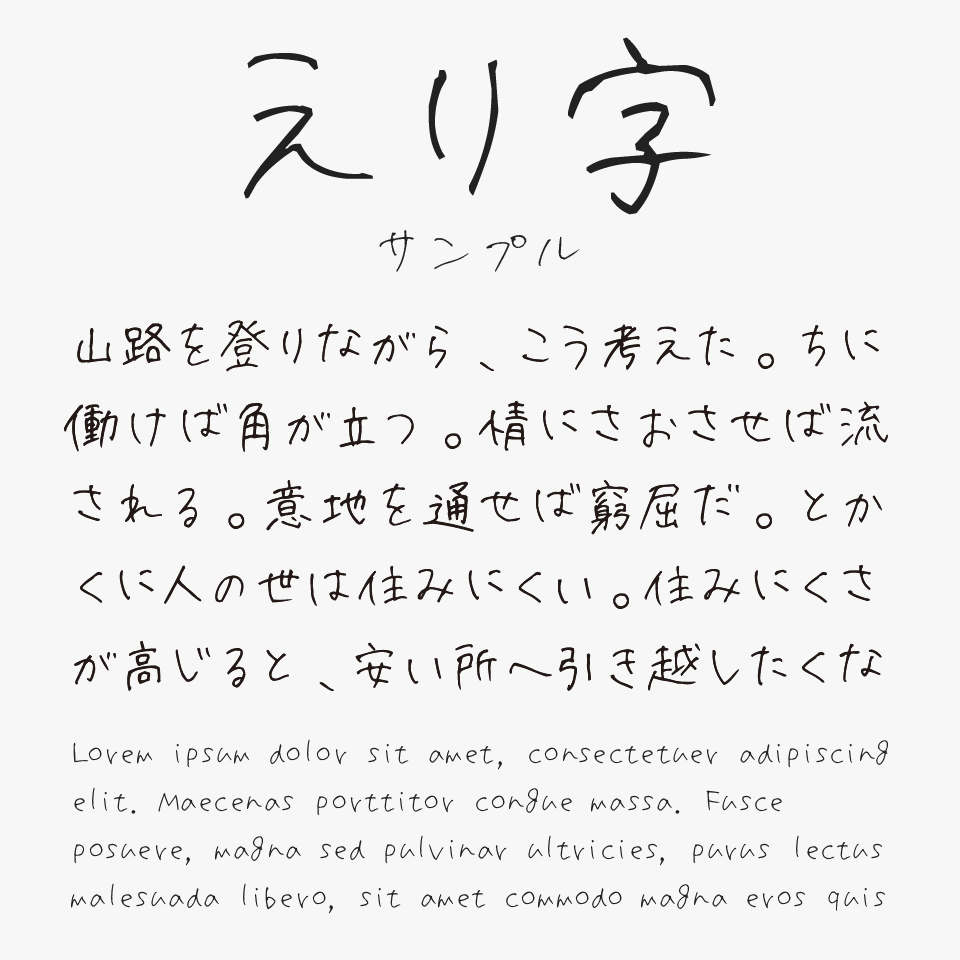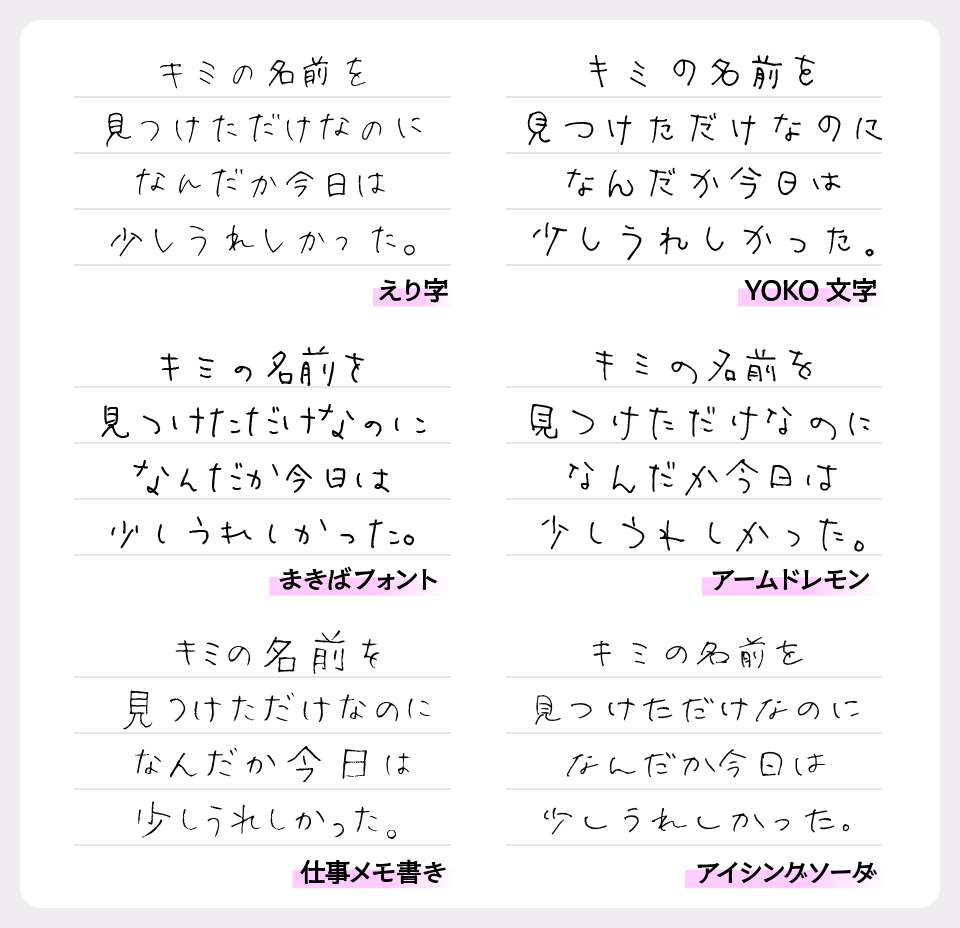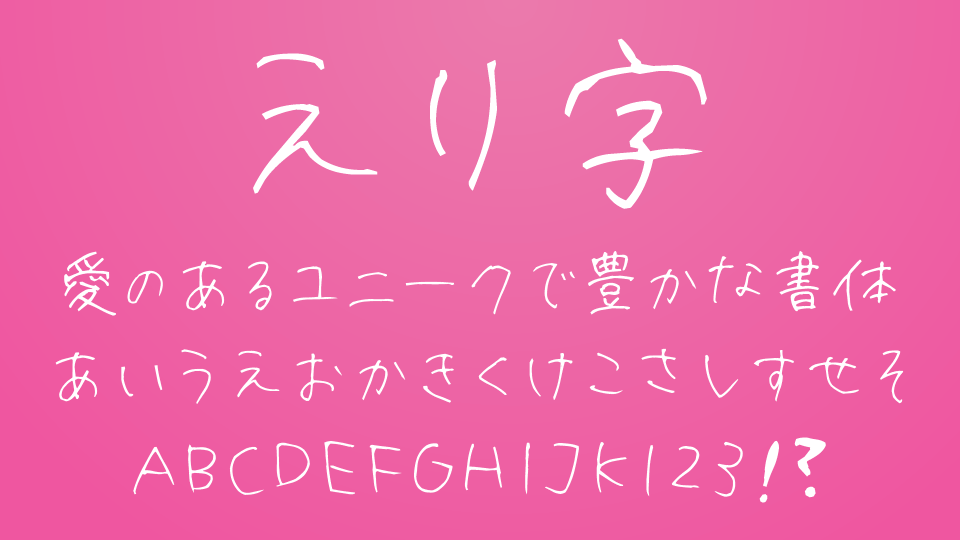
えり字
えり字フォントは、女子高生がボールペンでノートや手紙に書いたような、小ぶりで可愛らしい字が特徴の手書きフォントです。
文字全体に自然な丸みがあり、気取らない親しみやすさを感じられるデザインになっています。とくに、文字のハライ部分にはかすれ表現が取り入れられており、実際にボールペンで書いたようなリアルな筆跡が丁寧に再現されているところが魅力な手書きフォントです。
まるで誰かのノートをそのままフォントにしたような自然体の雰囲気がとてもステキです。手紙風デザインや雑貨系ビジュアル、SNS画像、ブログのアイキャッチなどとも相性が良く、リアルな手書き感を求めている方にとてもおすすめのフォントです。
えり字
ボールペンでサラサラと書いたような流れるような字は、きっちりとした硬さもなく、ゆるすぎる印象もない、幅広い年代やデザインに向けて使うことができる字になっています。
えり字フォントを、ほかのさらりと書いた雰囲気を持つ手書きフォントと比較してみると、リアルな筆跡感と素朴な可愛らしさが特に魅力のフォントです。
比較フォントは、「YOKO文字」「まきばフォント」「アームドレモン」「仕事メモ書き」「アイシングソーダ」と使用していますが、どのフォントも独特な脱力感+ゆるさもつ手書きフォントなので、ぜひあわせてチェックしてみてください。
えり字フォントと、、「YOKO文字」「まきばフォント」「アームドレモン」「仕事メモ書き」「アイシングソーダ」を比較
収録文字は、ひらがな・カタカナ・常用漢字からロシア文字まで幅広く収録されています。
文字幅は統一されています。